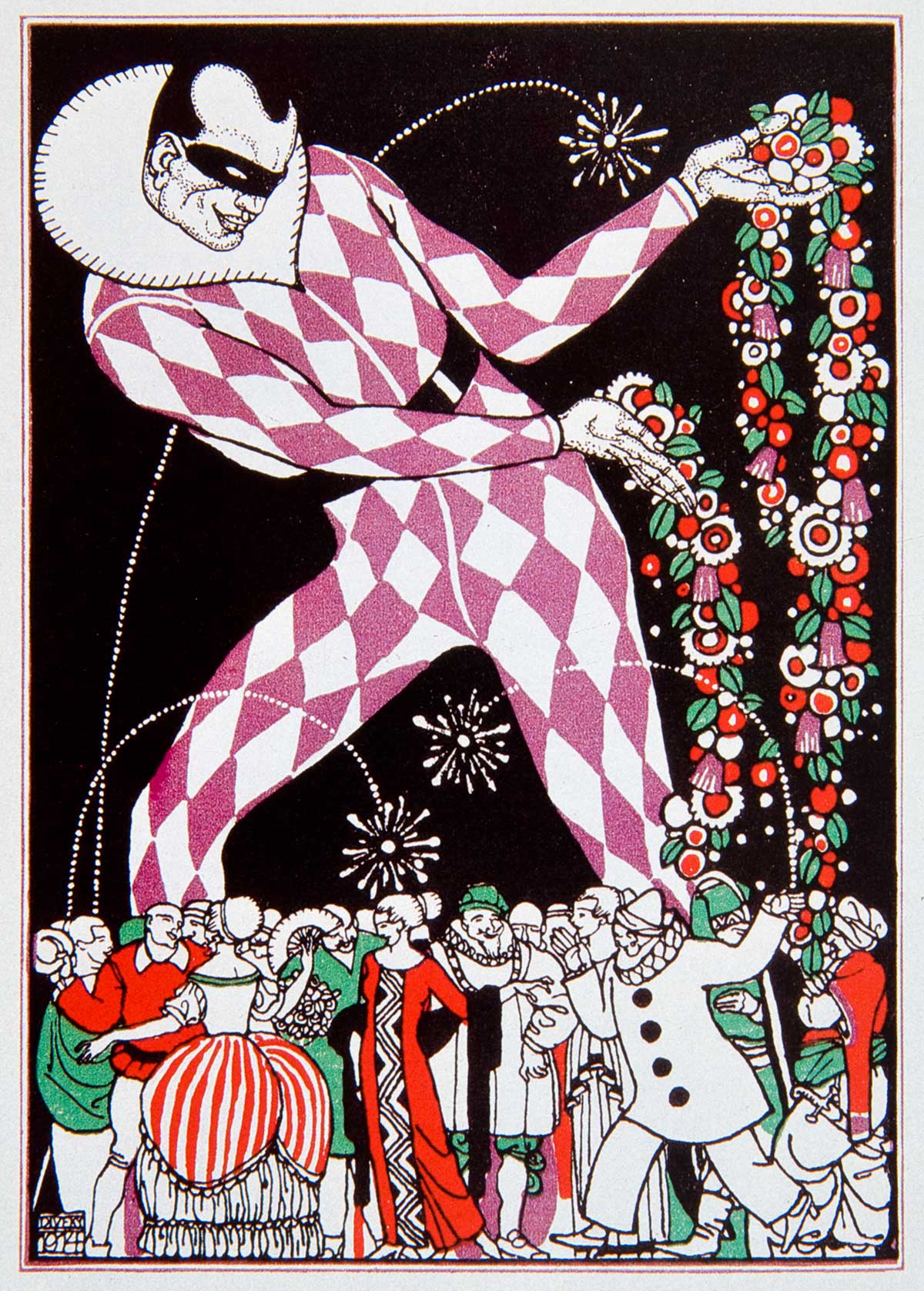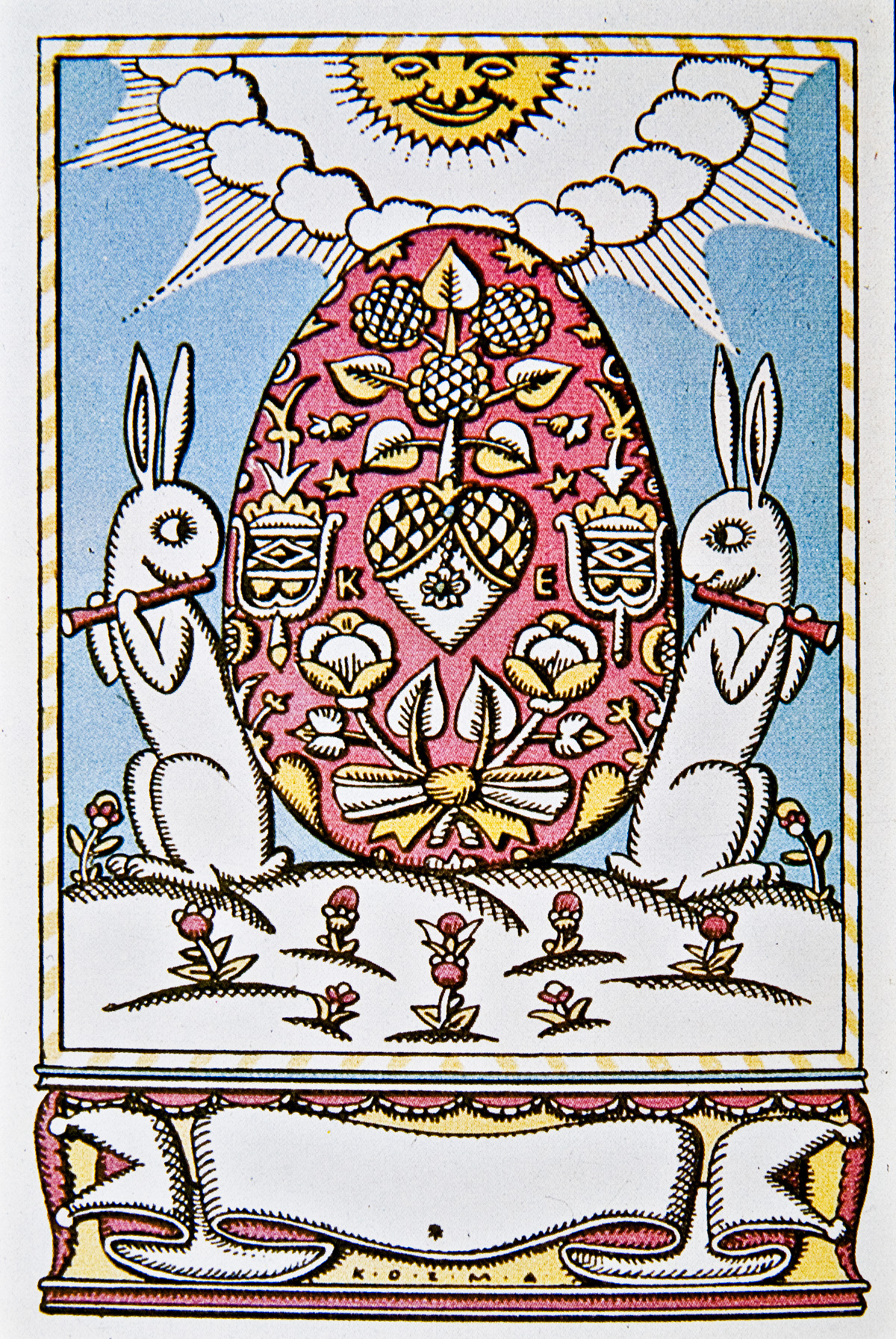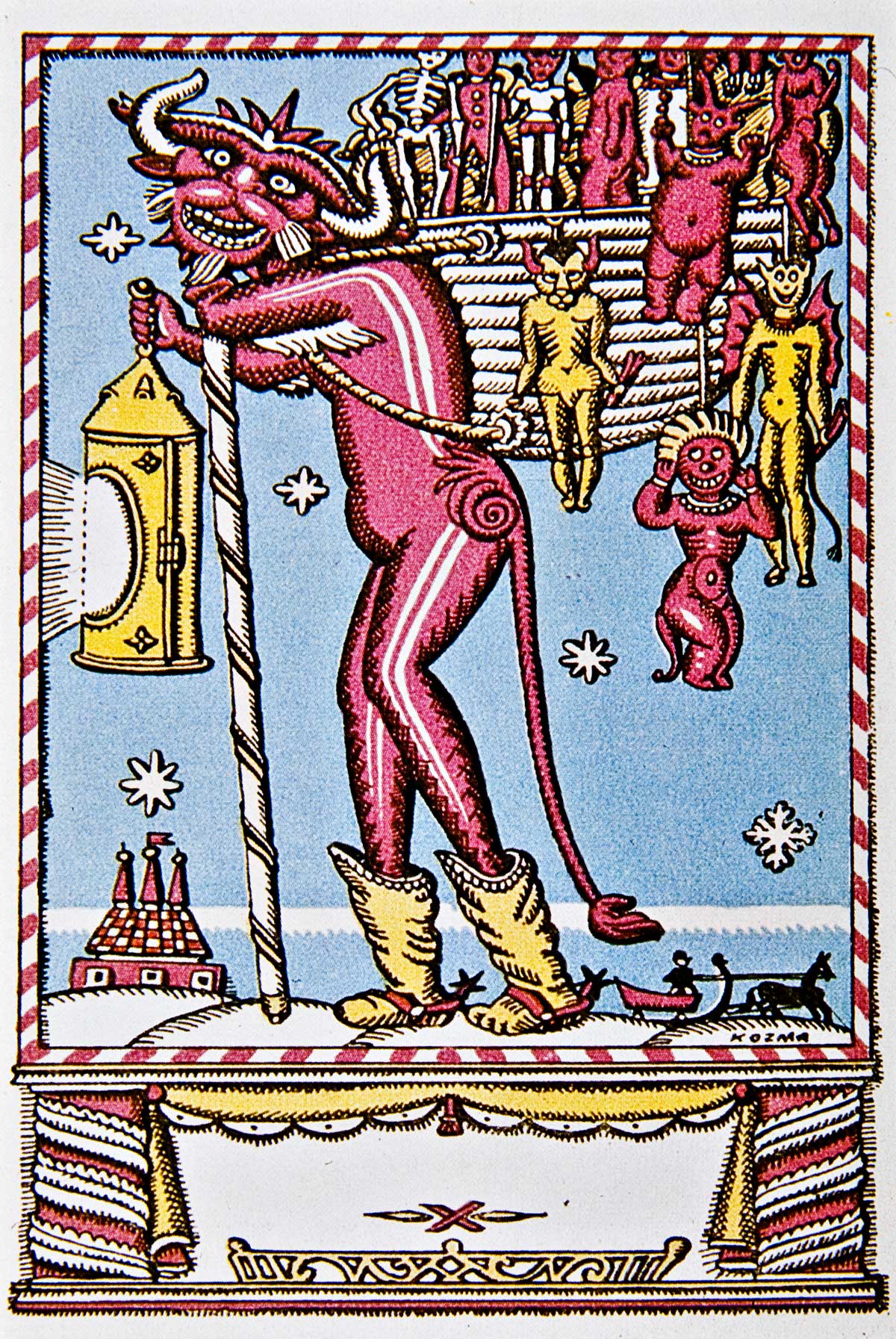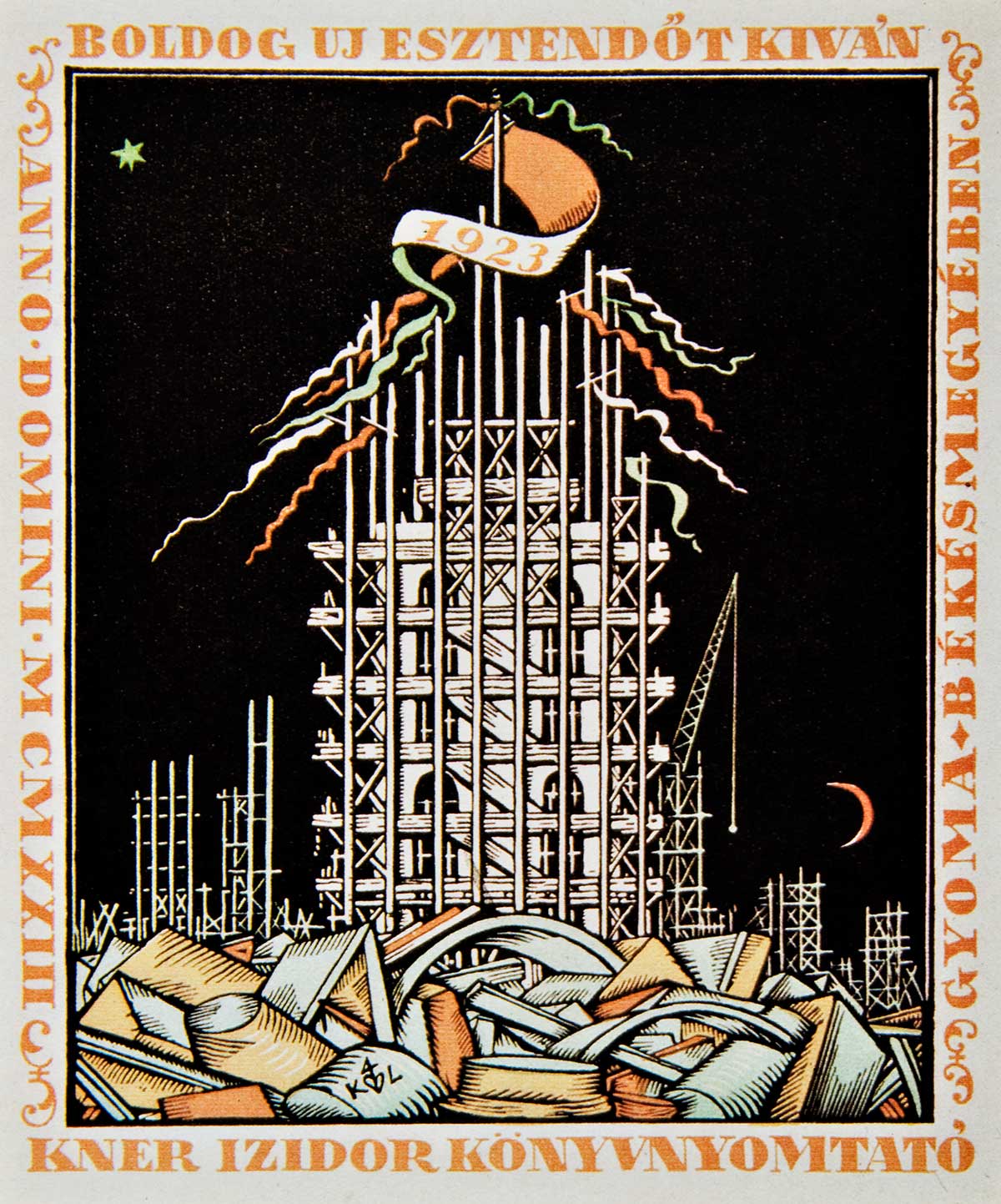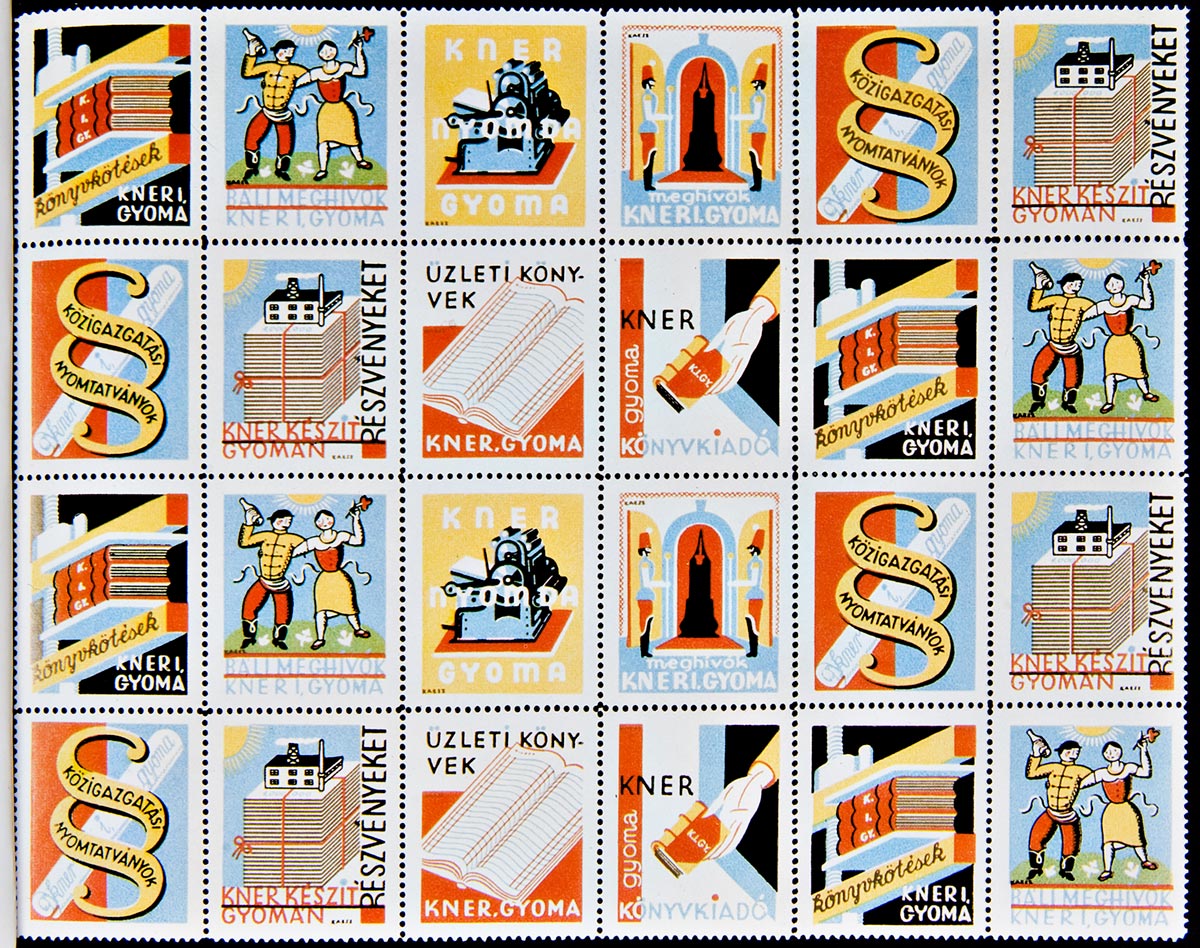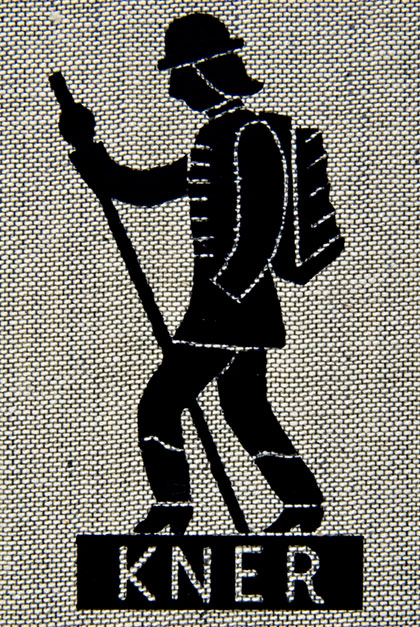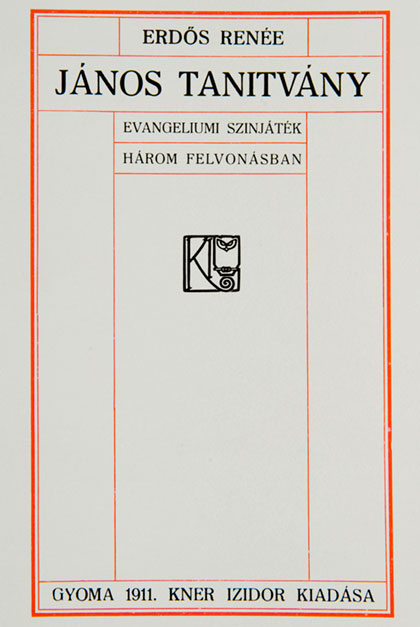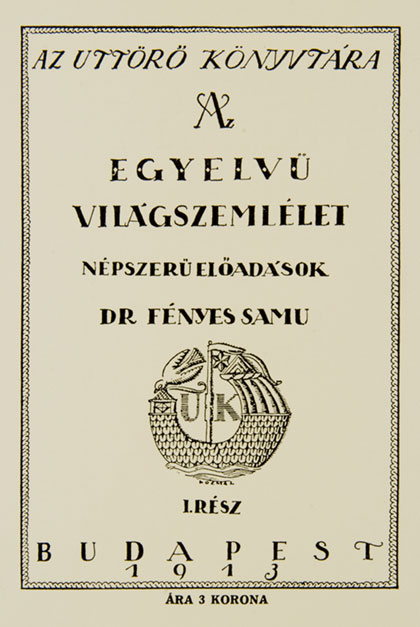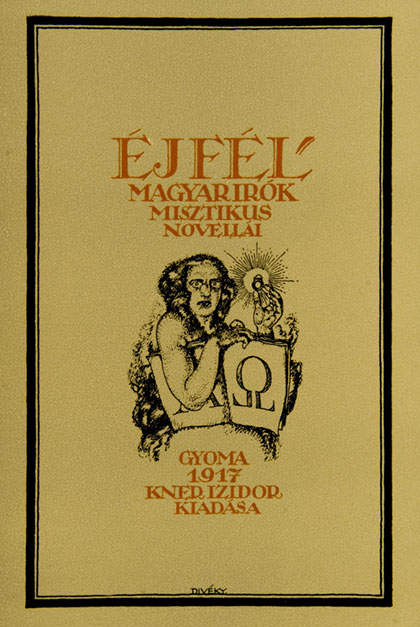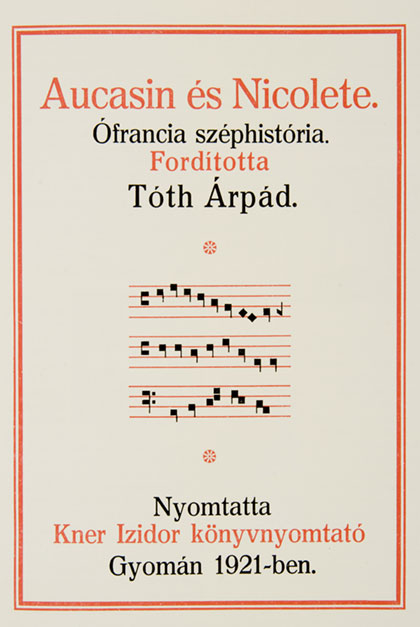
Kner, une famille d’imprimeur-éditeur magyare | 1882-1944 | 1/2
Je publie ce jour quelques reproductions d’un ouvrage assez rare concernant une des plus grandes familles d’imprimeurs que la Hongrie connût. Les Kner! Nous avions abordé dans le billet précédent quelques commentaires sur les trademarks, leur évolution depuis le début du XXe siècle. L’on voit bien d’après les illustrations ci-après le rôle et l’importance que jouent les imprimeurs dans l’histoire des logotypes modernes. Emblèmes de métier, ils firent dessiner nombre de personnages et de symboles pour ‘signifier’ leur corporation et leur ‘petite’ entreprise. La marque de fabrique des imprimeurs: un sujet d’importance que nous pourrions aborder un jour tant leur évolution a suivie celle de l’histoire des images de marque.
Juste pour ajouter à cette introduction: de fait la famille Kner, son œuvre immense dans le domaine de l’édition et des arts graphiques a eu un retentissement mondial. Albert Kner émigra aux USA après la guerre et continua de promouvoir l’excellence de son métier à New York.
Détail Couverture du Livre: La Famille Kner, et l’art de l’édition hongroise de 1882 à 1944 (mise en page par Haiman György)
Couverture de Kner Imre, composition avec des lettres et des lignes orthogonales.
Kozma Lajos, première maquette de couverture imprimé sur les presses de l’imprimerie Kner
Maquette de couverture de Divéky József
Maquette de couverture de Kner Imre
Typographié par Kner Imre et illustré par Kozma Lajos (vignettes, gravure sur bois)
Série de vignettes, gravure sur bois de Kozma Lajos (1920)
Typographie selon Fournier, XVIIIe, vignettes en bois
Maquette de Albert Kner (1926), gravure sur bois
Gravures sur bois, Albert Kner (1924)
Édition à compte d’auteur de Otto Conrad, texte de Marc Aurèle, un seul exemplaire fut imprimé en 1930.
Couverture pour un ‘spécimen’ de caractères plomb, 1895, Kner Izidor.
1909, maquette d’une enveloppe réalisée par le jeune Imre Kner (1909). Décoratif, usage des filets et aplats couleur et de quelques vignettes.
1911-1912, maquettes de papiers en-tête par Imre Kner.
1909, travail scolaire récompensé de Pechán József. Une invitation.
1909, Une invitation sur concours gagnée, maquettée par Darilek Harry.
Divéky József, maquette d’invitation, 1914.
Diósy Antal, maquette d’invitation, 1929.
Végh Gusztáv, Enveloppe, 1930.
Kozma Lajos, maquettes de voeux aux alentour de 1925.
Carte de voeux par Divéky József et Kozma Lajos
Emblèmes et sigles réalisés par les éditions Kner autour de 1935.
Timbres publicitaires (réclame) réalisés d’après les maquettes de Kaesz Gyula pour l’imprimeur-éditeur Kner
Où l’on découvre plusieurs choses: la Hongrie (Magyar Ország) a une grande tradition des arts graphiques et de l’imprimerie. Les œuvres ci-dessus démontrent la porosité des mouvements DaDa et suprématistes dans toute l’europe de la fin du XIXe et du début du XXe siècle. Une période faste pour la Hongrie d’avant l’annexion de l’Autriche-Hongrie par le régime Nazi. Il est tout à fait remarquable de trouver un éventail de polices de caractères plomb au choix le plus éclectique. Garaldes, Didones, Linéales, Manuaires fournissent à foison les casses des imprimeurs et les graphistes hongrois travaillent avec le même souci de perfection que leur collègue de l’ouest. Ils sont sous le charme d’un mélange de la tradition et de la modernité qui leur vient de l’Est et d’Allemagne. Les tendances se téléscopent, art déco, bauhaus, classicisme cohabitent dans le même temps. La Publicité s’appelait encore la Réclame mais le graphiste avait déjà compris la nécessité d’être efficace, ramasser les signifiants d’un message à leur expression la plus dépouillée. L’interruption forcée par la guerre ne changera rien à la marche de cette ultra sensibilité. Et les professionnels hongrois à l’instar de leur collègues polonais et tchèques déploieront force talent pour promouvoir la Nouvelle Société communiste jusqu’à ce jour historique où le mur de Berlin s’en ira en poussière et que ce pays rejoindra les structures politiques et économiques de la grande Europe. Pour un petit pays de dix millions d’âmes peu urbanisé dans ces temps reculés on peut sans conteste parler d’un miracle graphique à la magyare tant la qualité des œuvres se ressent d’une sensibilité universelle.